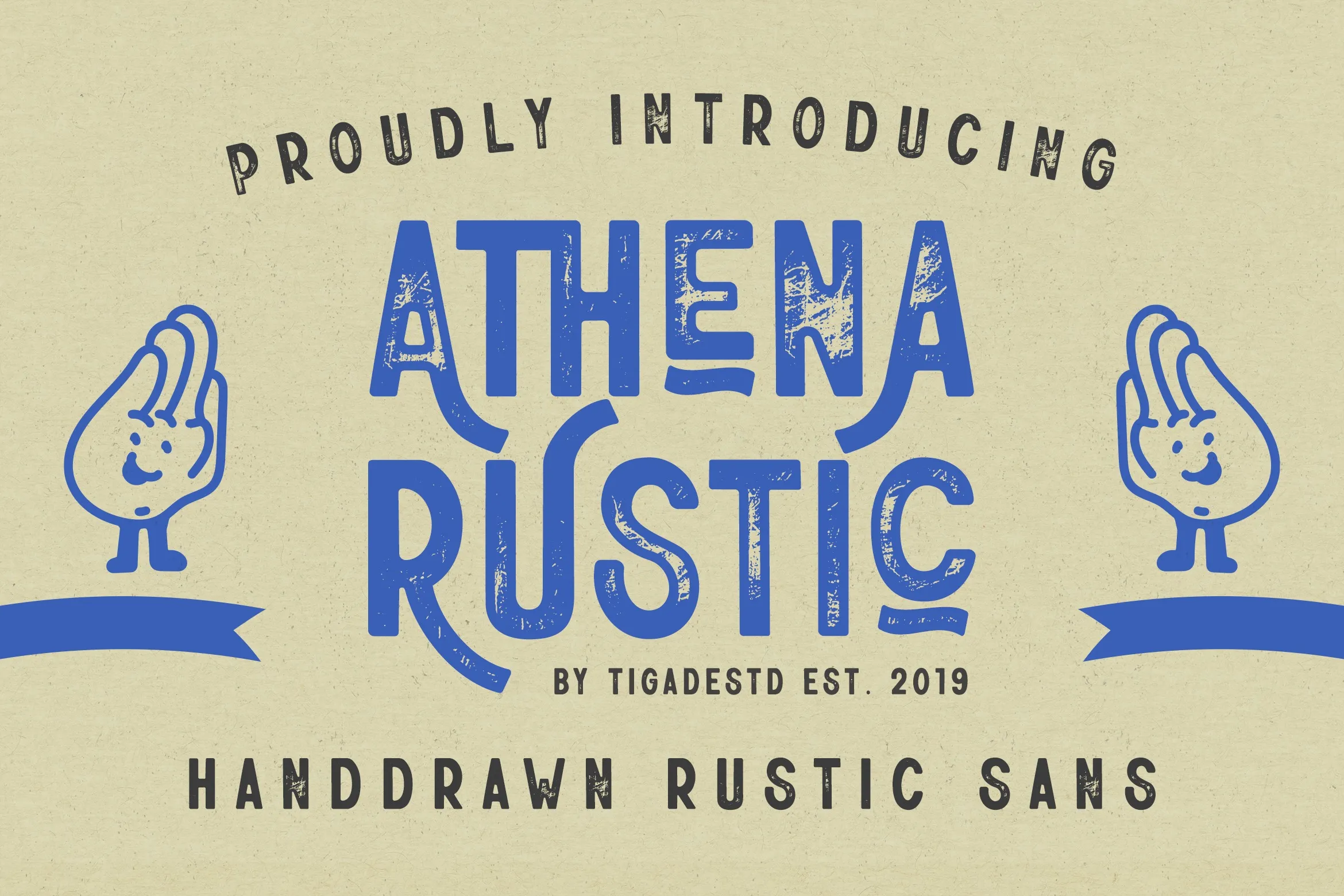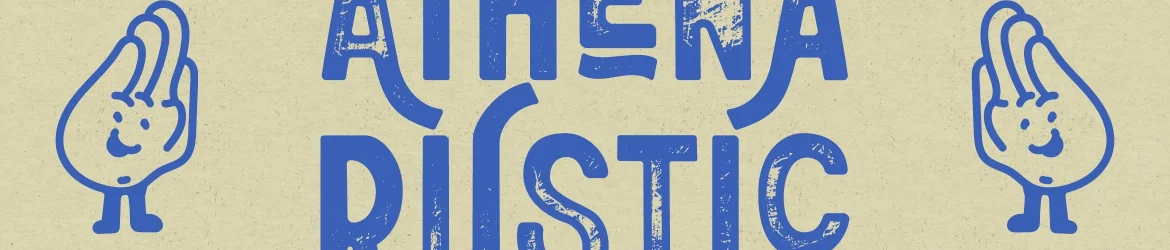
Athena Rustic Font – Download Grátis
A Athena Rustic Font é uma exuberante tipografia criada pela Tigadestd Type que oferece a essência elegante das fontes vintage, mas também o charme desenfreado do estilo retro. Com seu efeito rustico texturizado aplicado à cada caractere, foi realizada uma ilustração cuidadosamente manuscrita em papel para imitar o realismo natural dos traços. Este tipo é ideal para designers que buscam um equilíbrio entre elegância moderna e a nostalgia do passado. Sempre adequada tanto para design de aplicativos quanto para o layout gráfico, Athena Rustic fornece uma opção única para quem busca trazer uma personalidade única à sua arte digital.